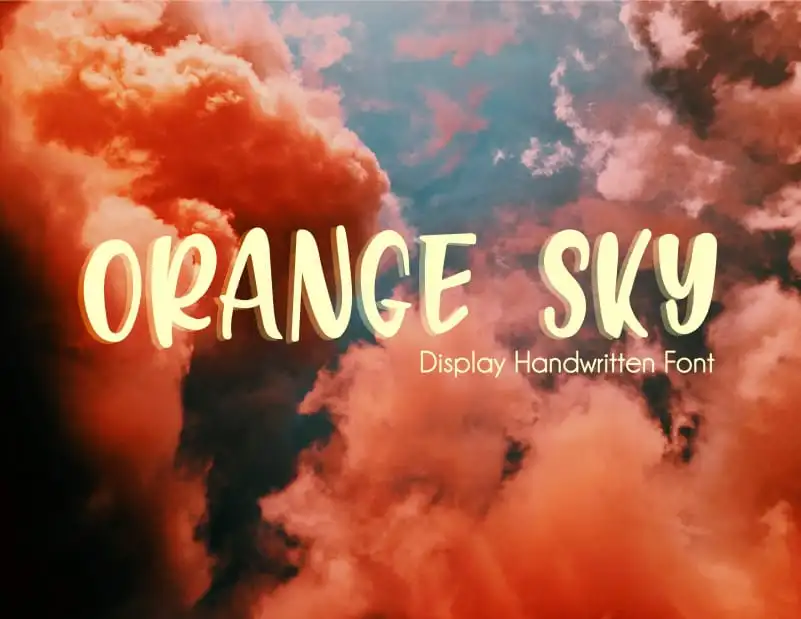
Orange Sky Display Font – Download Grátis
Aqui está uma versão descritiva do font Orange Sky Display Font para a categoria de handwrited fonts: Atravessando as ruas urbanas, onde os carros batem um papo lento com as luzes das acelerações, você pode encontrar uma linha que se desenha na atmosfera. Isto é o Orange Sky Display Font, um entrelaçamento de linhas suaves e formas arredondadas, reminiscente do frescor da manhã no Brasil tropical. Escrevendo com essa fonte dá a impressão de deixar sua impressão em papel como uma folha de árvore na brisa. Ela leva um toque de liberdade para suas letras, permitindo que seus usuários transformem frases simples em algo quase poético. Desenvolvido pela Fourth Lane, essa font é perfeita para anúncios, grafismos e até cartões personalizados. Suas linhas elegantes se desenrolam como um passeio pelas praias do sul do Brasil, onde o sol perto do horizonte brilha com aquele famoso arco-íris de cores. Portanto, não apenas uma fonte para o trabalho, mas também algo que você pode usar para expressar sua essência pessoal e dar vida à sua marca.